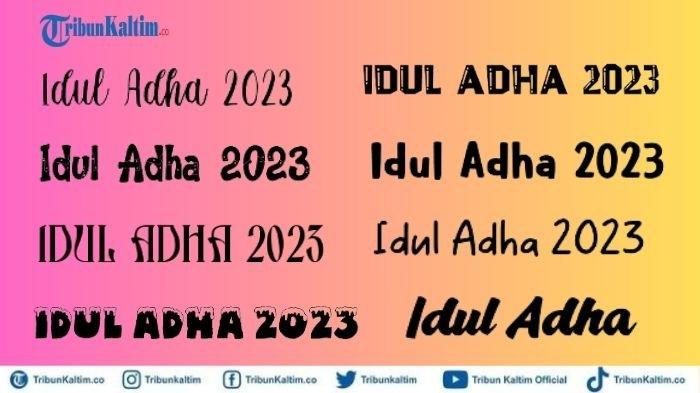
50 Link Font Estetik Tulisan Idul Adha 2023, Cocok untuk Background Hari Raya Kurban
Inilah kumpulan link download font Idul Adha dengan tulisan estetik yang cocok untuk background hari raya kurban.
TRIBUNKALTIM.CO - Inilah kumpulan link download font Idul Adha dengan tulisan estetik yang cocok untuk background hari raya kurban.
Kumpulan font terdiri dari nuansa islami yang cocok untuk membuat desain grafis Idul Adha 2023.
Diketahui, font merupakan tulisan yang memiliki ukiran/gaya tersendiri pada karakter tulisannya.
Sehingga, melalui font Idul Adha akan membuat desain seperti background hari raya semakin menarik.
Selain itu, font bisa disajikan ke dalam beberapa desain grafis bertema Idul Adha 2023.
Misalnya, gambar Idul Adha, twibbon, stiker, dan animasi GIF bergerak Idul Adha.
Font Idul Adha 2023